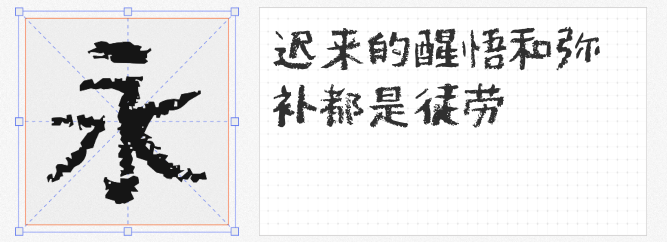
在恋爱类影视创作中,字体不仅是字幕工具,更是营造氛围、传递情绪的视觉符号。本期推荐四款免费商用字体,它们以圆润笔触、灵动细节和治愈气质,为浪漫场景注入怦然心动的少女感,助你精准拿捏观众的情绪G点。
1. 站酷快乐体
这款字体如同跳跃的糖果,笔划末端自然上翘的弧度与不规则的笔画粗细变化,自带俏皮表情。在校园告白、闺蜜谈心等轻快场景中,快乐体能完美烘托角色的雀跃心情。其手写般的稚拙感,尤其适配弹幕式花字或手账风排版,让观众瞬间代入青春悸动的情绪漩涡。
2. 仓耳非白 W03
看似硬朗的方整结构下,暗藏圆点与粗细对比的巧思。这款字体通过直角转折与圆形点画的碰撞,在工业风与软萌感间找到绝妙平衡。当画面需要表现“外冷内热”的角色特质,或打造科技感恋爱故事时,仓耳非白的5种字重可灵活切换,从轻盈对话到高甜宣言皆能精准传递。
3. 标小智龙珠体
以“龙珠”点睛的笔画设计,让这款字体成为甜蜜暴击的视觉载体。在告白特写、拥抱慢镜头等关键情节,将“喜欢你”“命中注定”等台词用标小智龙珠体呈现,圆润的笔画与跳动的龙珠装饰,如同爱情信号的具象化表达。其粗细渐变的笔触更带来速度感,适配快剪MV或回忆闪回片段。
4. PF频凡胡涂体
斑驳的蜡笔质感与不规则的笔触,赋予这款手写字体独特的复古浪漫。在暗恋独白、书信往来或跨时空叙事中,胡涂体能瞬间唤起观众的手作情怀。其略带沧桑的笔迹中透出的温柔,恰似被岁月发酵的暗恋情愫,为虐恋或久别重逢戏码增添厚重感。
这四款字体覆盖了恋爱剧集的全场景需求。建议根据剧情节奏混搭使用,形成完整的情绪叙事链。让字体成为隐形的表演者,与画面、音乐共同编织令人心动的恋爱物语。